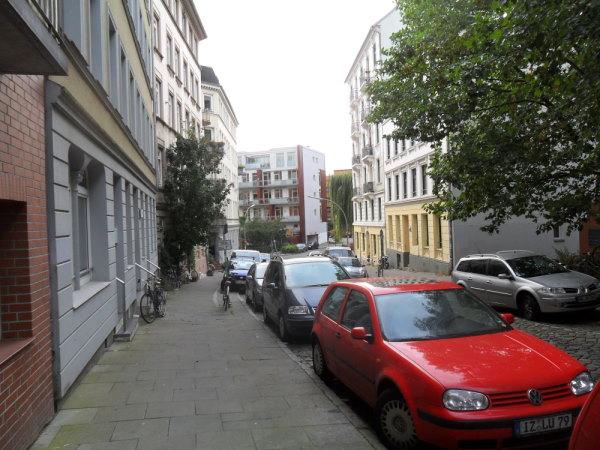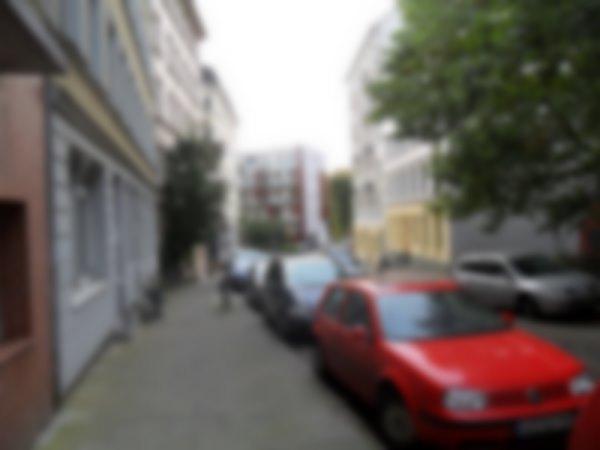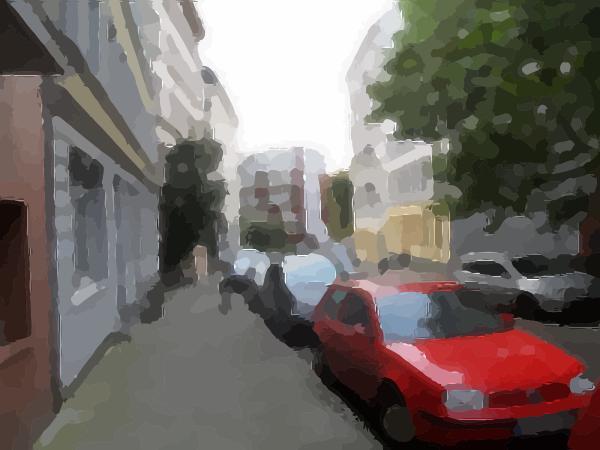
Darstellung von eingeschränktem Sehvermögen für Schriften etc.
ich suche eine Online Version zur Simulation des eingeschränkten Sehvermögens.
Man könnte es in Photoshop und Co. auch mit einem Weichzeichner machen, aber das wäre hier nicht möglich, da hier Linuxsystem vorherrscht. Gimp kann das zwar, aber hier soll es life gemacht werden. Hier geht es um die Lesbarkeit einer Schrift (Noto) die ich dem Vorstand eines Vereins vorlegen möchte, da die Hausschrift den Kriterien nicht entspricht. Diese Schrift soll für informationstafeln verwendet werden.
Noto ist eine freie Google-Schrift die sehr stark ausgebaut ist(über 1 GB download).
Mit "life" meinst du "online"? Ob du nun einen Browser startest oder Gimp, ist doch eigentlich egal … ?
Ja, so stellt sich das jemand vor, der gut sehen kann, aber ein Foto gesehen hat, das nicht im Fokus ist.
Ich weiß aber ziemlich genau, wie das wirklich aussieht, muss man sein Leben lang eine starke Brille tragen, und hat die gerade nicht auf der Nase, schließlich habe ich, seit ich etwa 5 war so etwa 6 Dioptrien auf der Nase.
Da liefert das Auge dann natürlich ein unscharfes Bild, aber das Auge liefert eigentlich auch ein Bild mit vielen Störungen, wie dem Adergeflecht auf der Netzhaut, dem Blinden Fleck und unterschiedlicher Dicht der Sehzellen. Trotzdem sehen wir ein glattes Bild unserer Umgebung, denn die eigentliche Bildbearbeitung, die dann unsere Wahrnehmung aus den Rohbildern, die unserer Augen liefert, werden im Grunde ähnlich, wie eine MPEG-Videokompression im Auge aus aktuellen, und kurzzeitig gespeicherten Bildern (quasi wie Keyframes) zusammengebaut.
Und das führt eben nicht dazu, dass ich ohne Brille ein verwaschenes Bild sehe, sondern eben das Ergebnis, was dabei heraus kommt, versucht unsere "Kopf-Grafikkarte" daraus ein uns scharf erscheinendes Bild zu berechnen. Dabei sind deutliche Kanten dann auch tatsächlich scharf begrenzte Kanten, während Dinge, die das unscharf falsch fokussierte Auge nicht mehr aufzulösen vermag, verschwinden dann teils komplett aus der Wahrnehmung, so dass einfach nur feine Details verschwinden. Das Bild gleicht dann irgendwie einem impressionistischen Gemälde.
Ich habe das mal versucht nachzustellen:
1. das scharfe Originalbild:
2. Was das Auge sieht, nehme ich die Brille ab:
Und was meine "interne Bildbearbeitung daraus macht...
Schaue Dir auch ruhig noch einmal diese Fontliste an:
Ich denke für Dein Projekt dürfte auch die Fira Sans interessant sein.
nicht wirklich, da der Vorstand kein Gimp auf dem Tablet hat.
Wenn Du damit das Weichzeichnen im Browser meinst, sollte das heutzutage kein Problem mehr darstellen.
Robert der @Ralf Herrmann hat ja sowas mal programmiert um die Lesbarkeit seiner entwickelten Schriften zu testen. Da er dieses Programm nur für Mac programmiert hat, kann es nicht verwendet werden. Wir können auch nicht beliebig installieren da jedesmal der Admin durch die ganze stadt fahren muss. Ist leider nicht alles unter einem Dach.
Vielleicht hast mich missverstanden. Ich weiß ja nicht genau was Ihr vorhabt, aber man könnte diesen Weichzeichner eben direkt auf einer Webseite implementieren – das Know-How eines Programmierers vorausgesetzt.
Ah so. Ich dachte, du wolltest das präsentieren …
Dieses Foto habe ich mir dann mit und ohne Brille betrachtet, dieses Empfinden mit den trotzden scharfen Konturen, nur eben mit fehlenden Details, habe ich dann so gut es ging auch mit Vektorisierung nachgebaut. Wenn man also keine feinen Details benötigt, merkt man daher die Sehschwäche gar nicht so. Daher ist es auch recht schwierig, zu erklären, wie man mit Fehlsichtigkeit tatsächlich die Welt sieht, weil es eben nicht wie eine nicht scharf gestelle Kamera wirkt. Darum wollte mneine Mutter auch nie, das ich mich mit Grafik beschäftige, und hat mir das Schriftmusterbuch, das sie im Laden hatte, als ich ca 14 war auch wieder weg genommen und verkauft. Sorry, Mama! Das Interesse daran konntest du mir letztlich doch nicht nehmen...